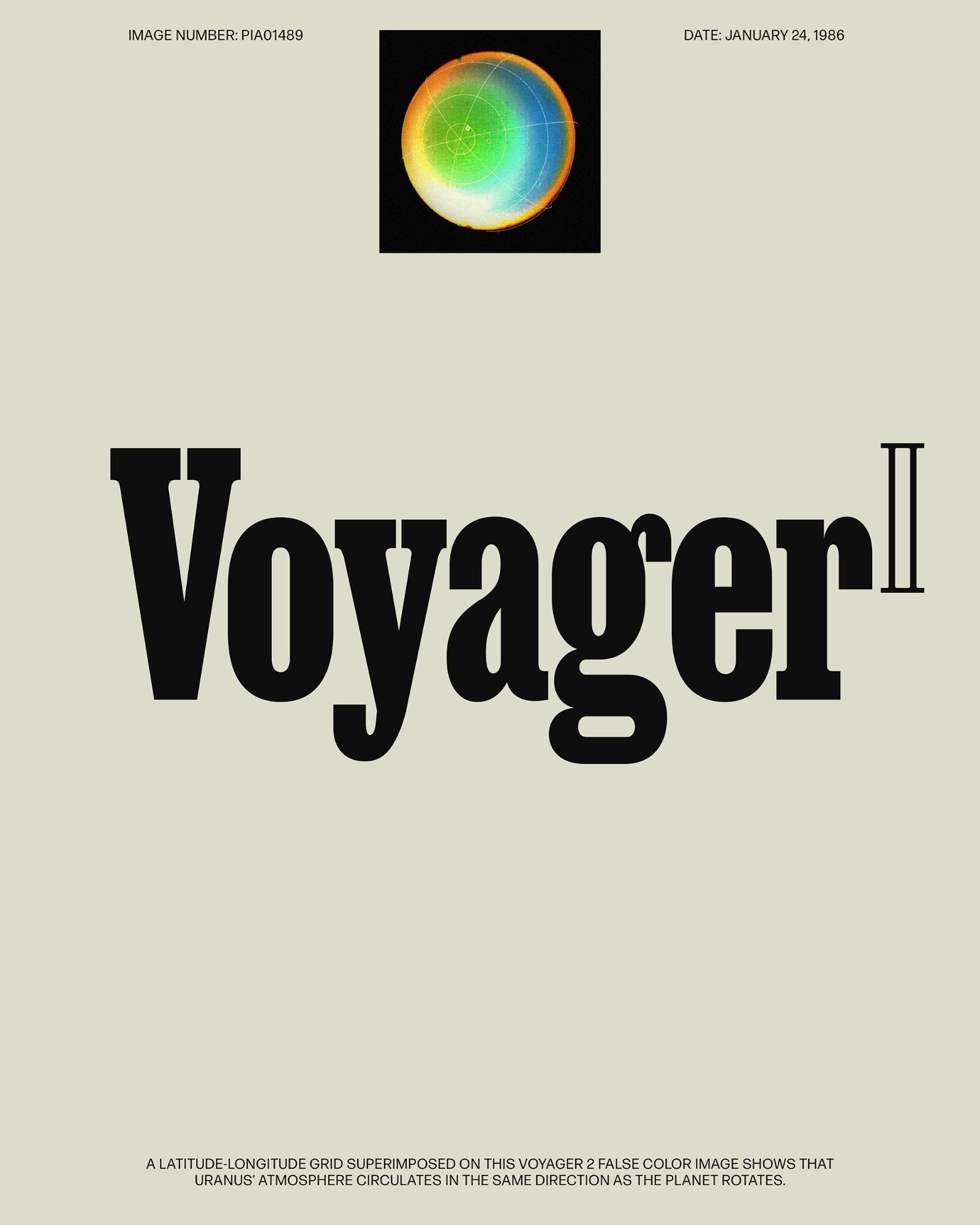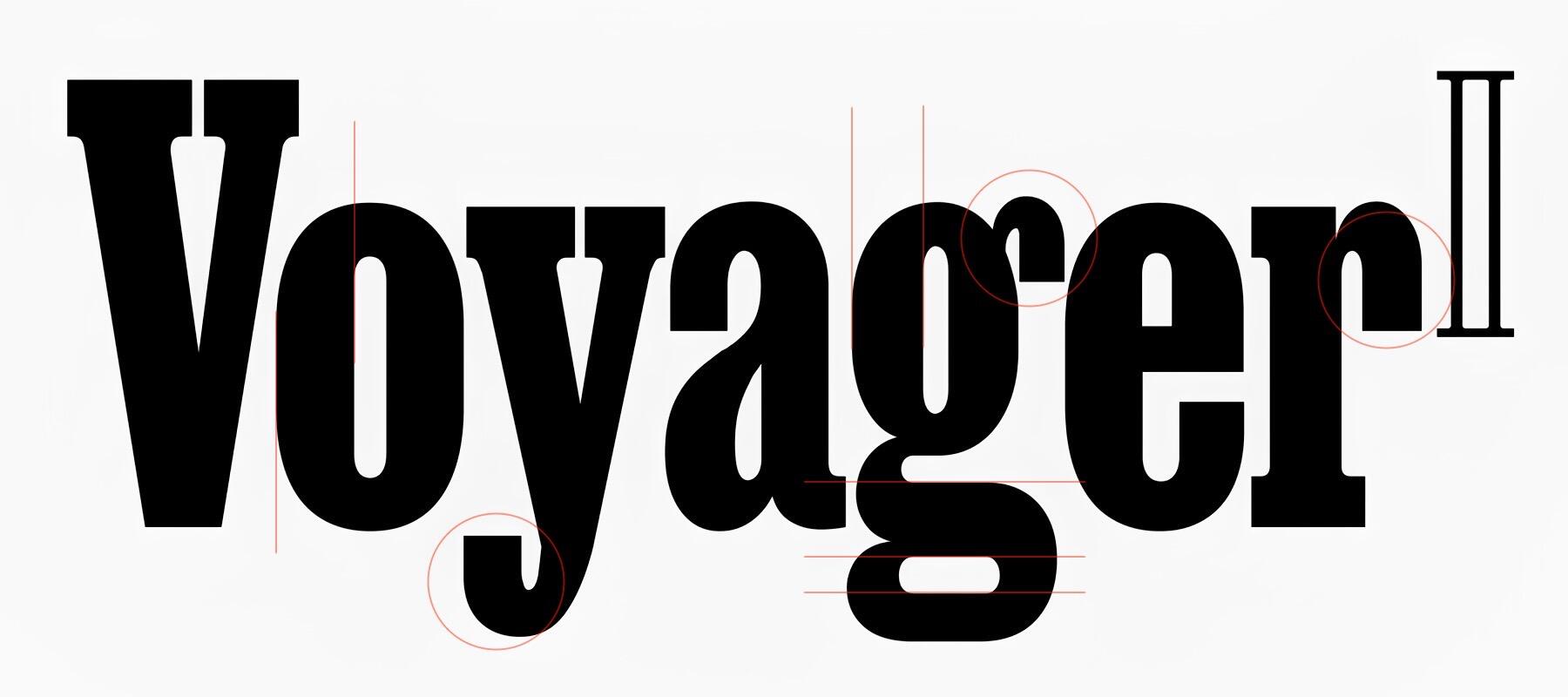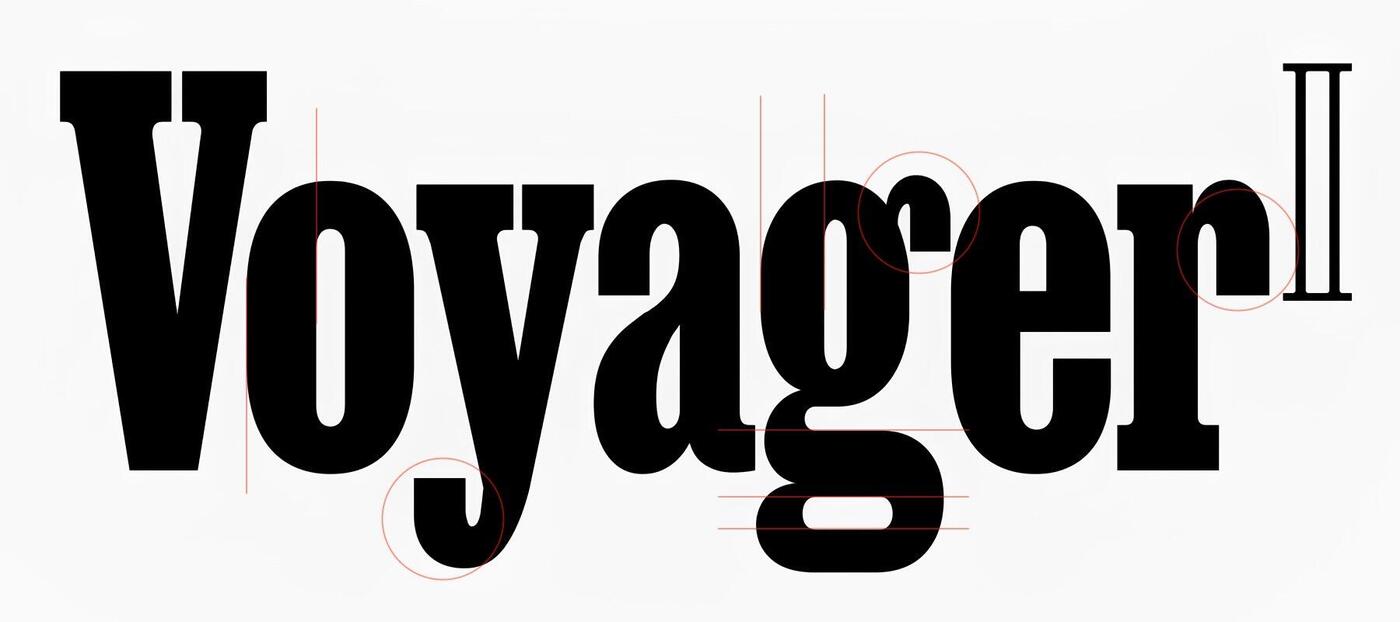
Bitte um Schriftidentifikation: schmalfette Egyptienne (NASA Voyager II)
erster Beitrag, hobbytypophiler Amateur hier, bitte Milde walten lassen. :–) Kennt jemand folgende Schrift?
Das folgende Muster hatte ich irgendwann gespeichert, Tineye und ich können die Quelle aber nicht mehr finden, und es gibt auch keine verwertbaren Metadaten. Die Datierung (1986) deutet aufs vordigitale Zeitalter, aber wenn es sich wirklich um einen Scan handelt, ist es der sauberste, den ich je gesehen habe.
Bislang konnte ich zwar mit Hilfe der einschlägigen Webseiten (Whatfontis, MyFonts, Fontspring etc.) einige ähnliche Schriften finden, aber keine Übereinstimmung. Also, für sachdienliche Hinweise wäre ich echt dankbar!